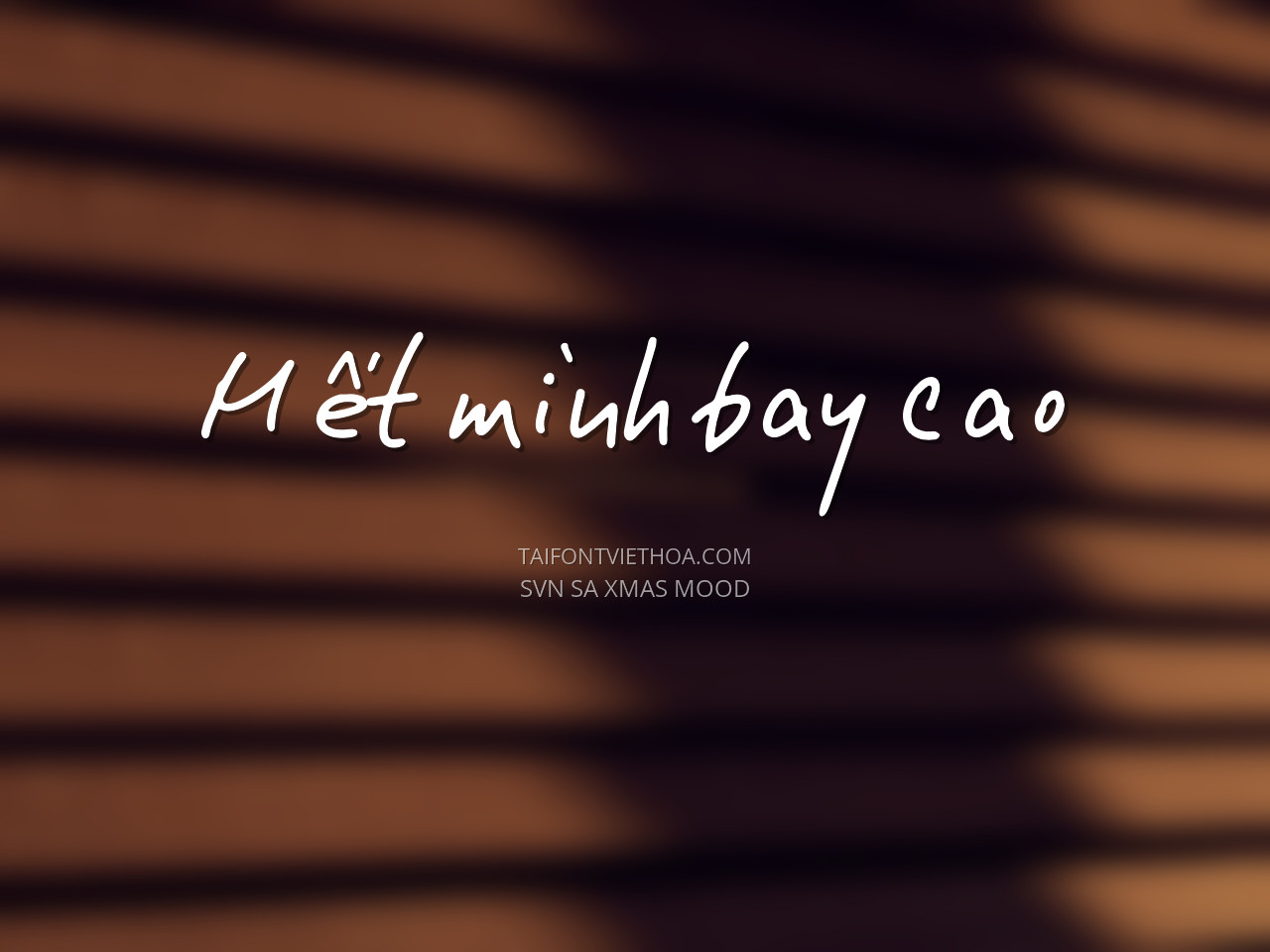
Giới thiệu về Sa Xmas Mood – Font display Giáng Sinh vui nhộn, ngộ nghĩnh
Sa Xmas Mood (tên gốc: Sa Xmas Mood Typeface) là phông chữ display sáng tạo lấy cảm hứng từ không khí lễ hội Giáng Sinh, được thiết kế bởi Typeline Studio(Indonesia) và phát hành trên Creative Market năm 2021. Font gây ấn tượng với các đường nét tròn trịa, chi tiết tạo hình vui nhộn, mô phỏng những món đồ trang trí Noel, cây thông, hộp quà và các biểu tượng mùa lễ hội. Bản quốc tế của Sa Xmas Mood hỗ trợ trên 60 ngôn ngữ Latin, đi kèm alternates, ligatures và ký tự đặc biệt, giúp font dễ dàng ứng dụng cho các ấn phẩm chủ đề Giáng Sinh hoặc truyền thông sự kiện lễ hội cuối năm.
Phiên bản SVN Sa Xmas Moodđã được STYLEno.1 FontsViệt hóa trọn bộ, bổ sung dấu tiếng Việt, tối ưu kerning và hinting để hiển thị sắc nét trên mọi nền tảng thiết kế. Đội ngũ taifontviethoa.comđã kiểm thử thực tế trên Photoshop, Illustrator, Canva… đảm bảo font không lỗi dấu, không vỡ nét kể cả khi dùng làm tiêu đề lớn hay thiệp mời nhỏ. Sa Xmas Mood Việt hóa là lựa chọn lý tưởng cho các dự án sáng tạo cần không khí Giáng Sinh tươi vui, truyền cảm hứng mùa lễ hội cho mọi ấn phẩm số và in ấn.
Đặc điểm thiết kế, ứng dụng và ngành nghề phù hợp
Sa Xmas Mood thuộc nhóm display – chủ đề Giáng Sinh, với cấu trúc chữ tròn trịa, bo góc mềm mại, các ký tự cách điệu mang lại cảm giác vui nhộn, ấm áp. Font còn tích hợp nhiều alternates và ký tự đặc biệt để trang trí, giúp cá nhân hóa poster, banner, thiệp mời hoặc story social media chủ đề Noel. Sa Xmas Mood phát huy hiệu quả khi dùng cho ấn phẩm quảng cáo lễ hội, bao bì sản phẩm Giáng Sinh, thiệp chúc mừng, sticker, hoặc các sự kiện cộng đồng, trường học, cửa hàng mùa lễ hội.
Ứng dụng tiêu biểu
– Poster & truyền thông:Banner Giáng Sinh, poster sự kiện Noel, story social media, catalogue sản phẩm mùa lễ hội.
– Thiệp & ấn phẩm nghệ thuật:Thiệp chúc mừng, bao bì quà tặng, nhãn mác sản phẩm, sticker Giáng Sinh.
– Trang trí & sự kiện:Background sự kiện Noel, trang trí shop, trường học, siêu thị mùa lễ hội.
Ngành nghề phù hợp